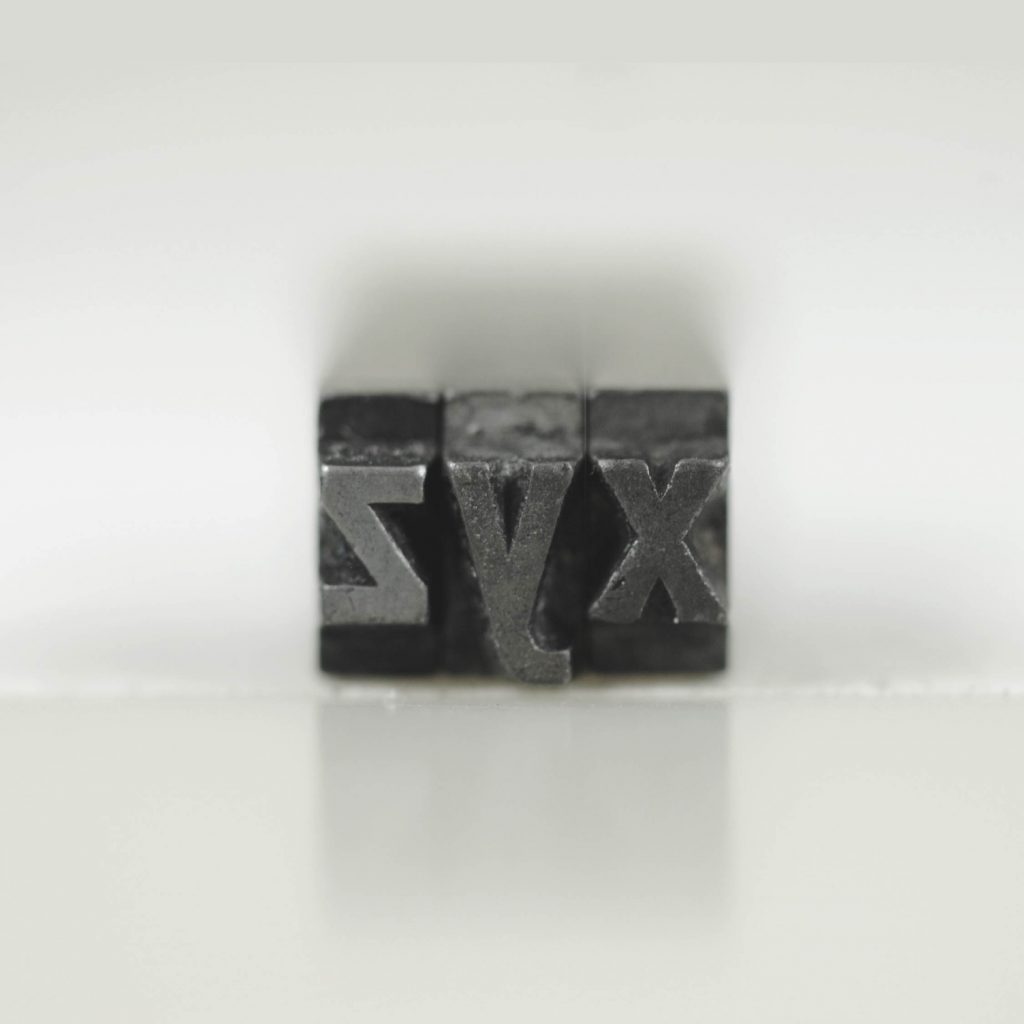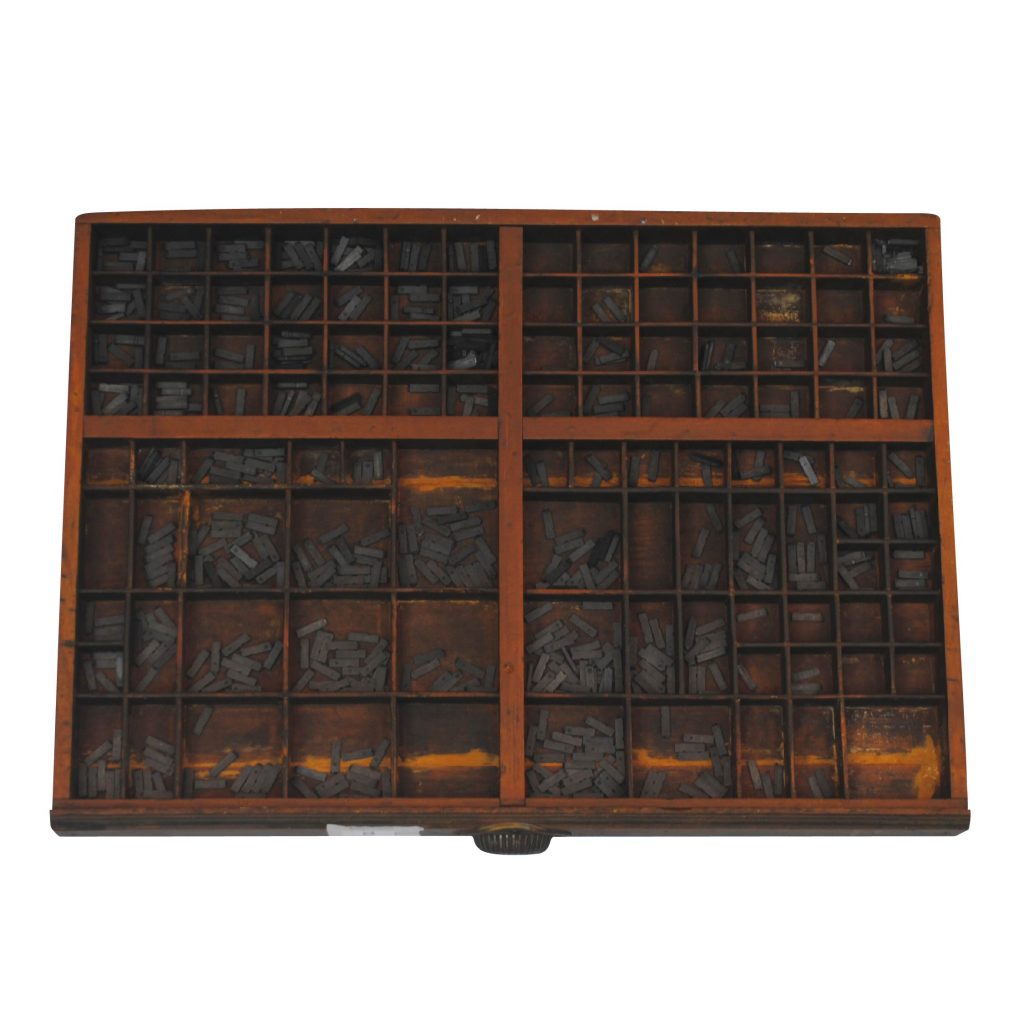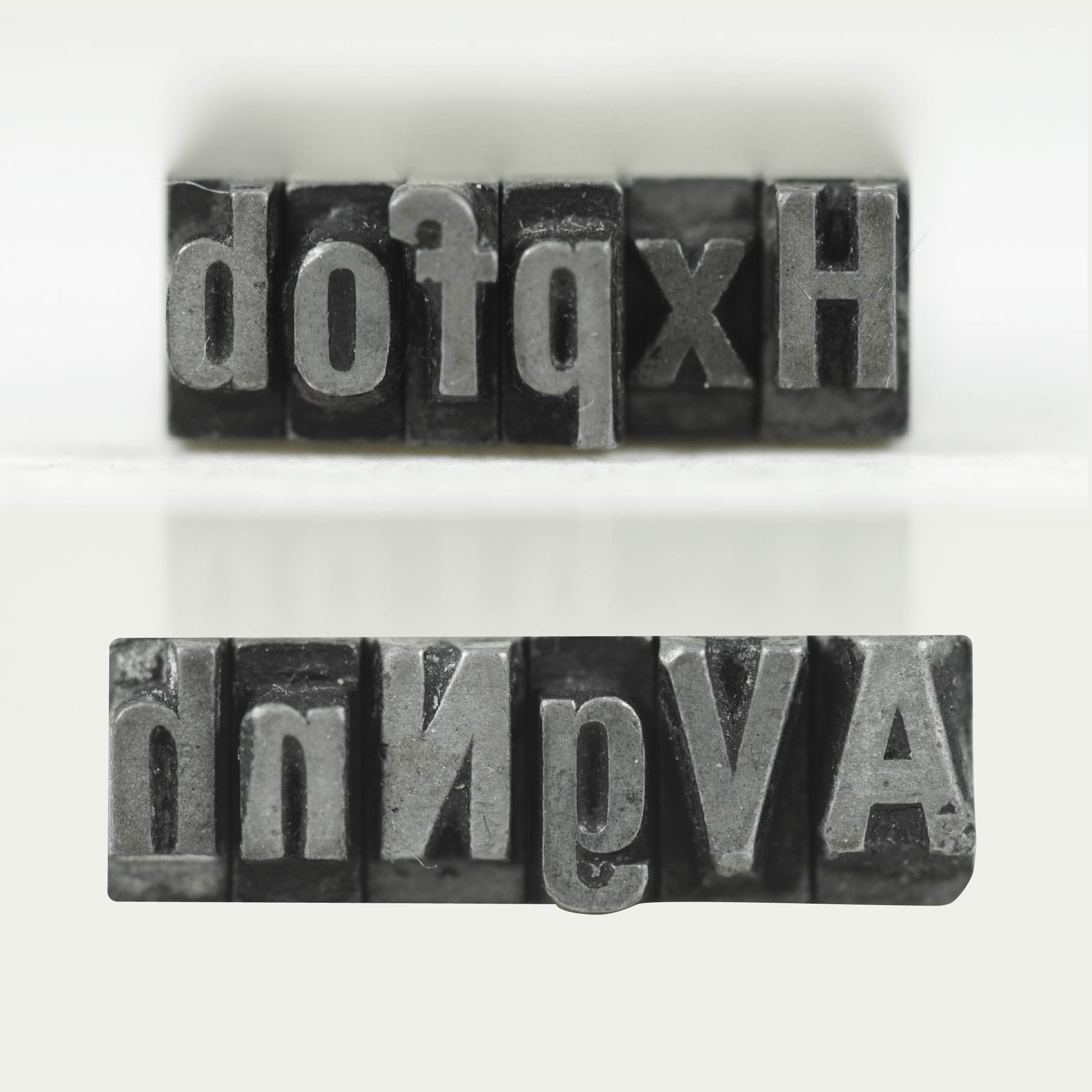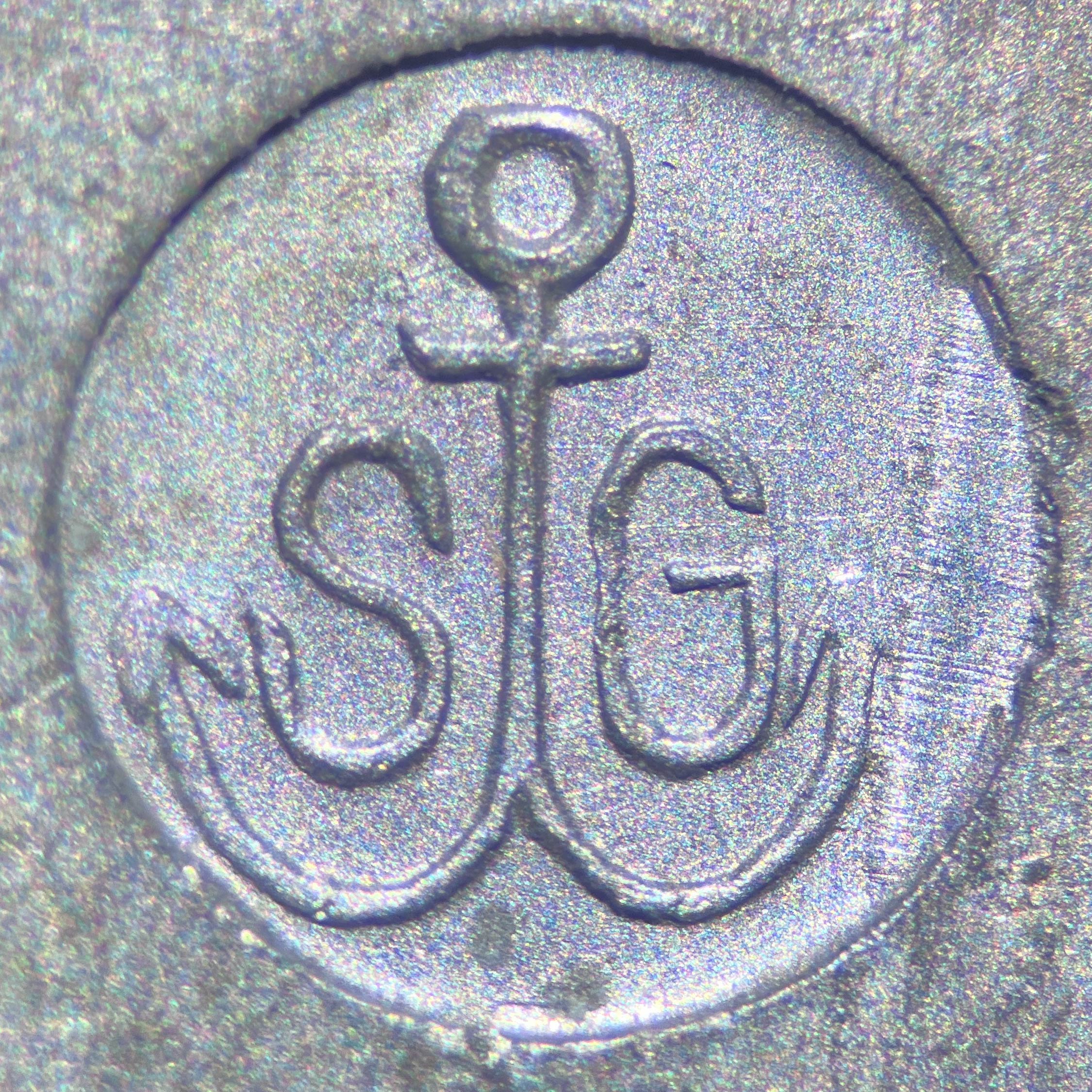
Steinschrift I_ character -
Steinschrift I_ ah -
Steinschrift I _ ae -
Steinschrift I _ $ -
Steinschrift I _ ç -
Steinschrift I _ ij -
Steinschrift I _ xyz -
Steinschrift I_grotesca 16_ post_ 6
Identificação
Steinschrift I 16pt
Estilo
Grotesca
Caracteres Chave
Acentos triangulares e pingos quadrados
Fundidora
Schelter & Giesecke
Tipo de Inscrição
Marca de fundidora
Localização da Inscrição
Face direita
Estado de Conservação
Marcas de uso recorrente; alguns tipos apresentam desgaste na face que pode comprometer a qualidade da impressão.
Disponibilidade
Maiúsculas | Minúsculas | Maiúsculas acentuadas | Minúsculas acentuadas | Numerais | Ligaturas
História do Estilo
Foram encontradas duas fontes semelhantes presentes no catálogo de tipos da fundidora J.G. Schelter & Giesecke (1912), a Steinschrift I.
Garnitur e a Steinschrift II. Garnitur (também conhecidas apenas pelos nomes Steinschrift I. e Steinschrift II.).
Após análises, foi constatado que se trata da primeira opção. Segundo Wetzig (1926), essa fonte foi comercializada por diversas fundidoras de língua alemã com pequenas variações nos desenhos e nos nomes. O nome utilizado pela fundidora remete à “inscrição em pedra", em tradução livre, o que configura um descritivo de suas características.
Observações do Pesquisador
A fonte inclui “ñ”, utilizado na escrita de idiomas como espanhol, quechua, tagalog, entre outros (Bringhurst, 2018, p. 348).